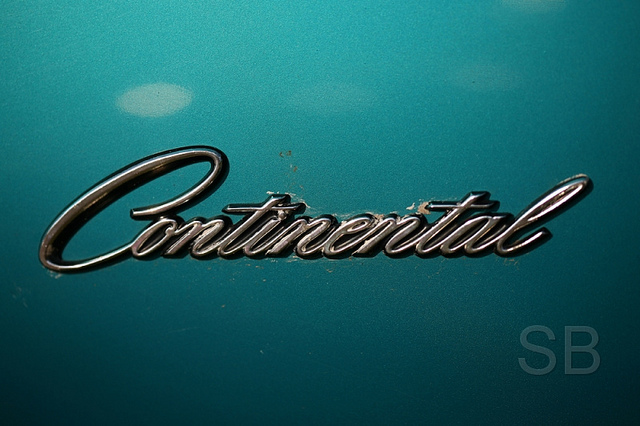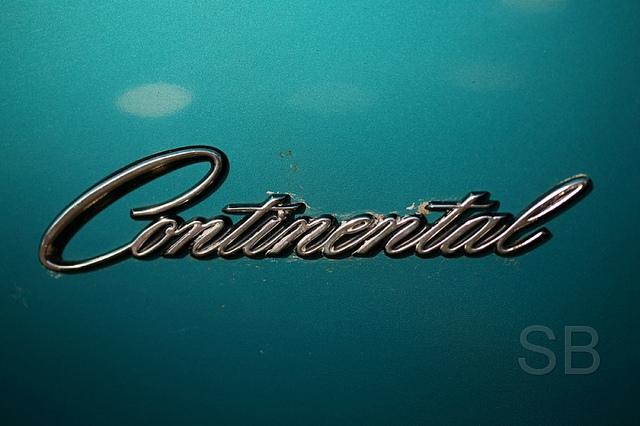
Schriftart des Oldtimer Emblems Lincoln Continental
ich bin auf der Suche nach dem Namen der Schreibschrift des Lincoln Continentals. Gewöhnlich ist der Schriftzug "Continental" als Chromeemblem auf dem Kofferraum der MarkIV und MarkV Reihe zu finden. Im Anhang befinden sich einige Bilder des Schriftzuges.
Falls es sich um eine auseigene Schriftart handelt, die man so nicht käuflich erwerben kann, wüde ich mich auch über ähnliche Fontnamen freuen.
Schon Deine Beispiele sind ja alle unterschiedlich, und auch alles gezeichnete Schriftzüge. Für ähnliche Schriften wirst Du für Beispiele 1 und 3 mit einer Suche nach Englischen Schreibschriften fündig, für Beispiel 2 vielleicht hier.
Derartige Sub-Markenlogos waren in dieser Zeit typische Arbeiten kaligrafisch tätiger Grafiker. Mein Onkel (Gustav Peyk) hat auch von derartigen Aufträgen gelebt.
Dass das nicht »eine Schrift« ist, sieht man schon daran, dass alle drei gezeigten Schriftzüge völlig unterschiedlich sind.
Wenn es also wirklich um eines dieser Logos geht, dann muss man das nachbauen. Es gibt keine Schriften, die auf solchen speziell angefertigten Schriftzüge passend würden.
Ähnliches:
Schreibschriften dieser Art hat Sudtipos viele:
Eine Übersicht von Fonts, die auf Mid-Century-Autoschriftzügen beruhen, gibt es im Wiki: